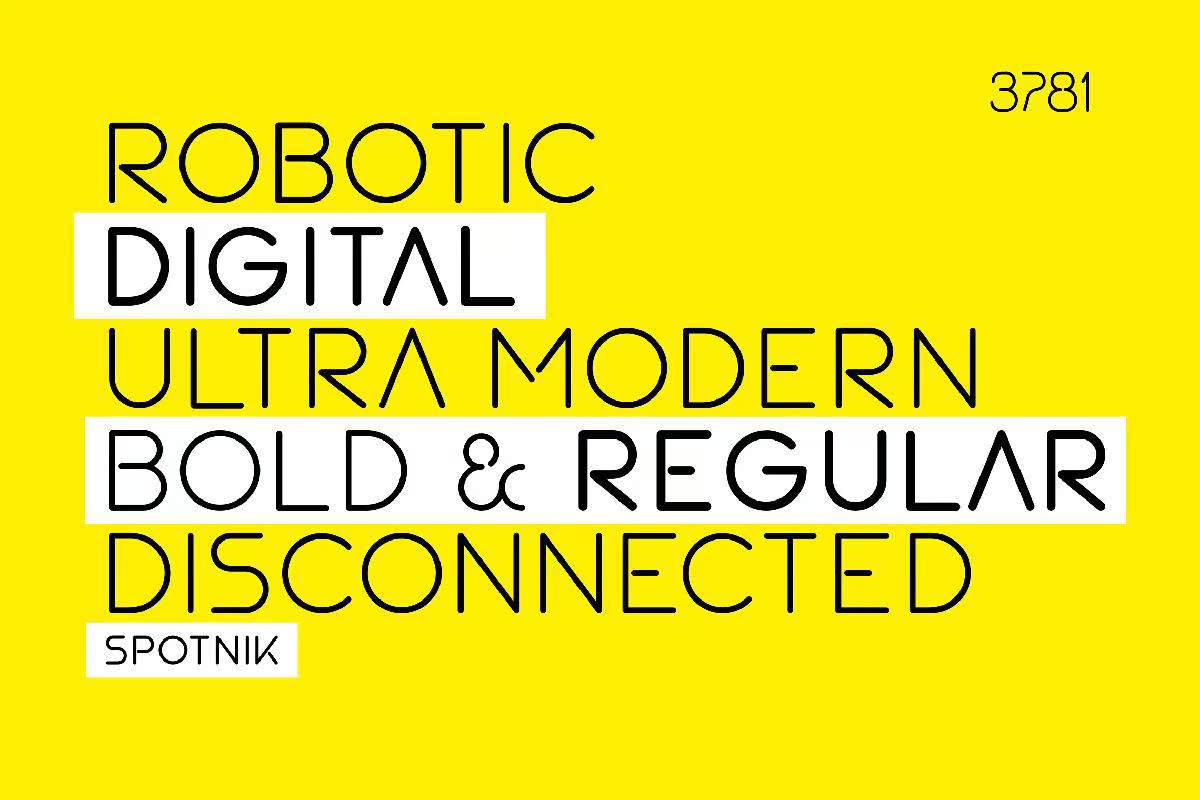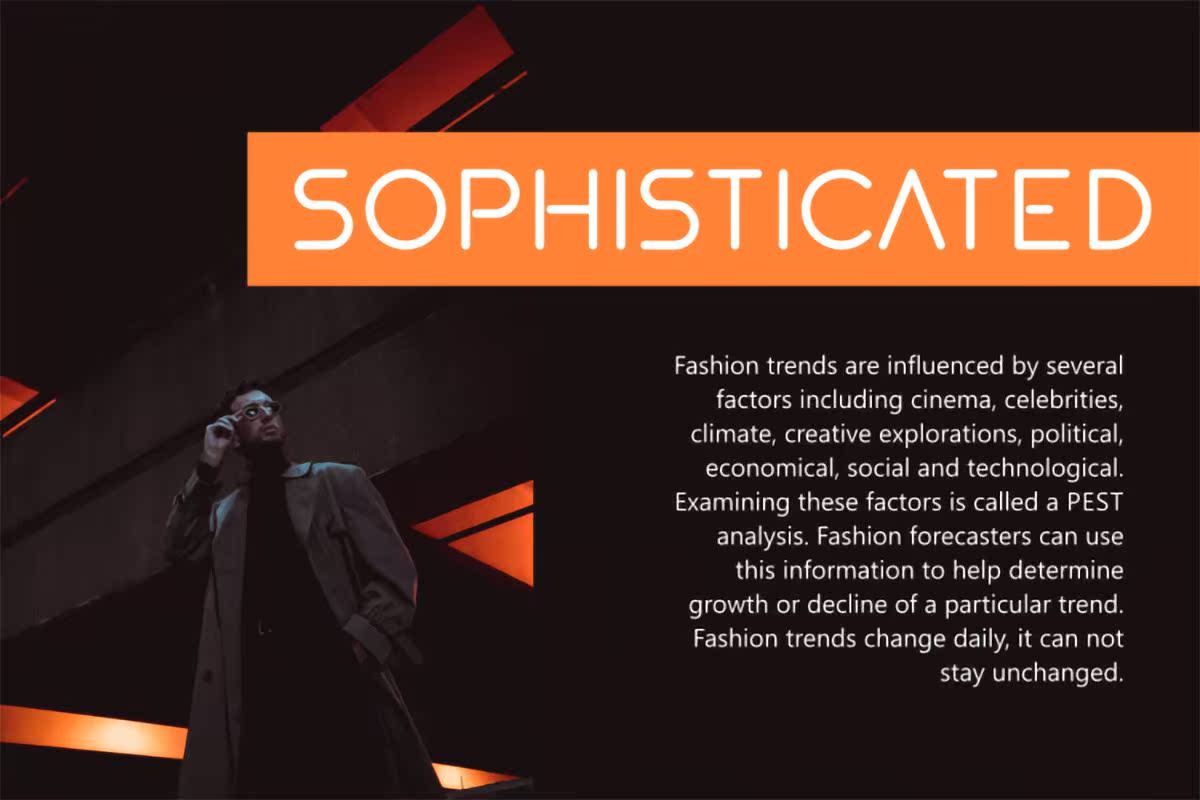
Freespotnik Sanseries提供了一种具有线性和开放连接方式的计量字体。它代表了现代技术和未来。它适用于您的设计项目,包括徽标、编辑、排版和网站。此强大的字体可用于TFormat文件,可帮助您安装在您的设备上。但是,此免费Demofont仅适用于个人使用许可证。但是,如果您想要更多功能,可以购买PremiumVersion。